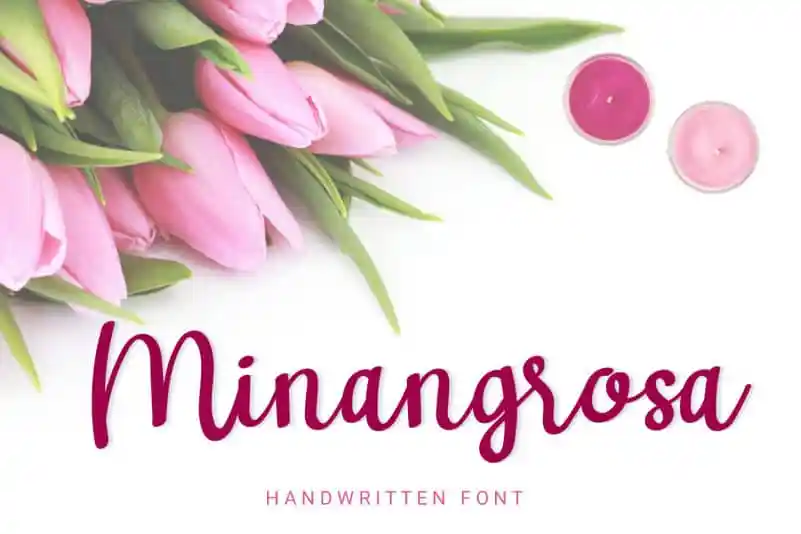
Minangrosa Handwritten Font
A Minangrosa Handwritten Font é uma elegante tipografia escrita à mão, com traços fluidos e delicados. Esta fonte teve suas raízes no coração do Brasil, onde a cultura é rica em histórias e emoções fortes. Suas curvas suaves se encaixam perfeitamente para criar cartões de aniversário elegantes, arte de cartão personalizada ou postagens memoráveis nas redes sociais. Estes detalhes sutis são ideais para qualquer projeto que exige um toque delicado e pessoal, seja ele uma celebração romântica ou simplesmente um momento agradável com amigos. Adquira já e adicione esse charme à sua próxima criação!